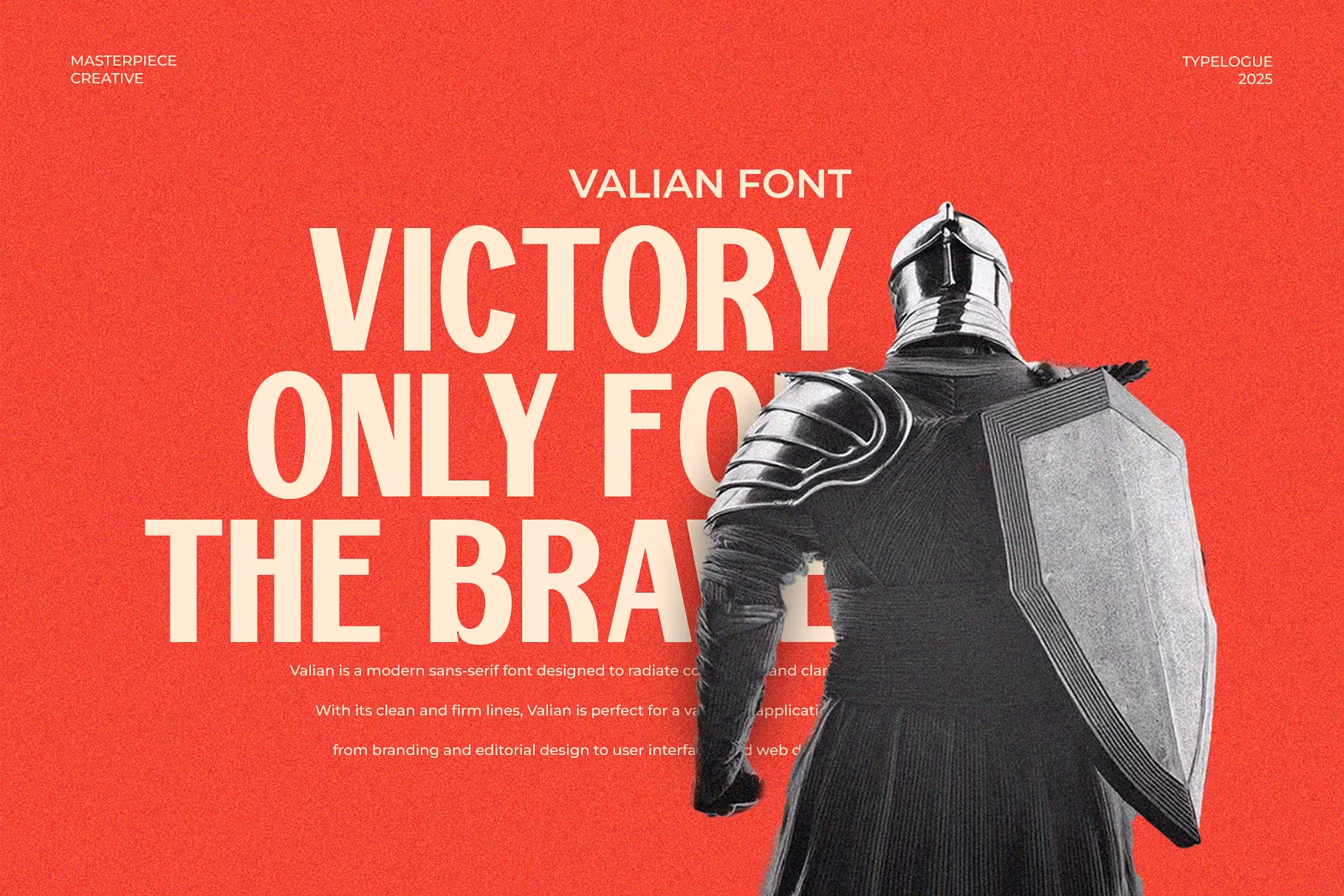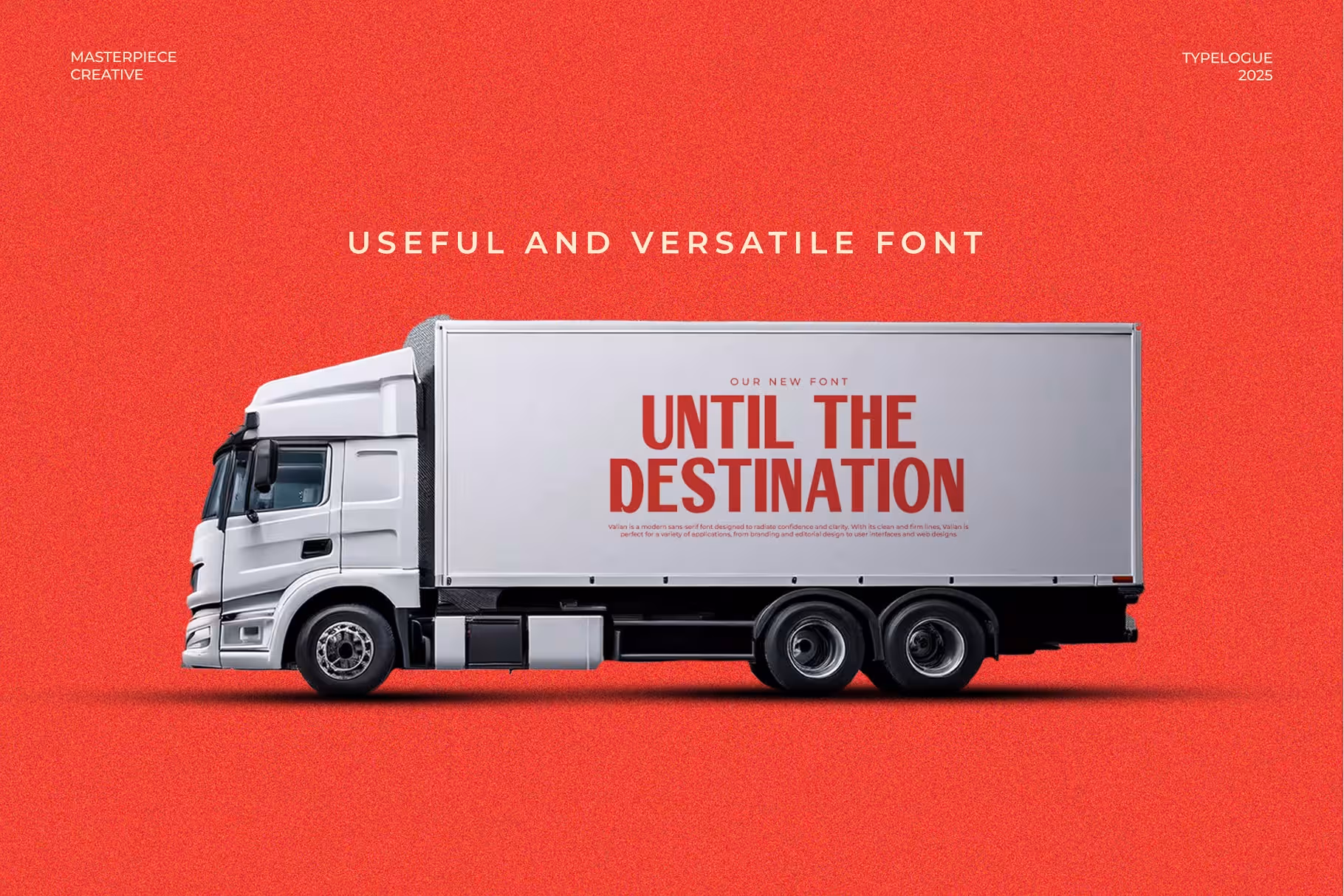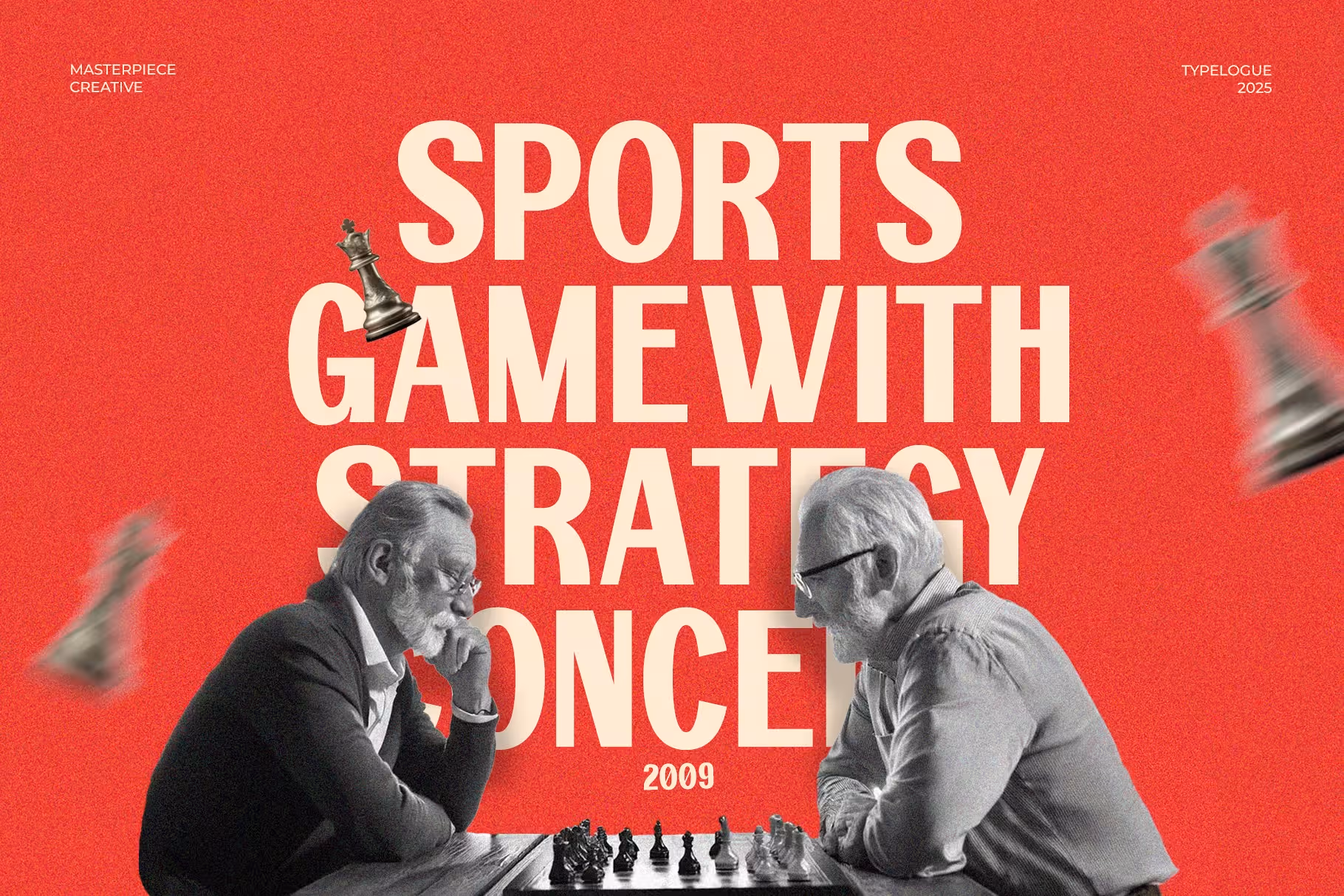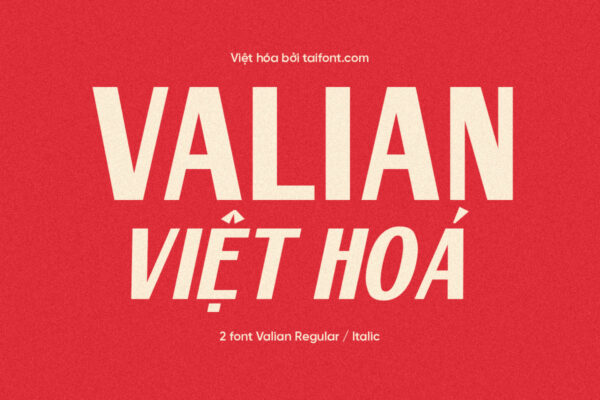
Giới thiệu về Font TF Valian Regular & Italic Việt hóa
TF Valian Regular & Italic Việt hóa là một bộ font chữ không chân (sans-serif) nổi bật với thiết kế mạnh mẽ, cứng cáp và mang phong cách cổ điển, gợi cảm giác về những bảng hiệu cũ kỹ, quảng cáo thời xưa hay những dòng chữ được in ấn một cách dứt khoát. Font này toát lên vẻ vững chãi, bền bỉ và đầy cá tính, lý tưởng để tạo điểm nhấn độc đáo và thu hút mọi ánh nhìn trong các thiết kế đòi hỏi sự mạnh mẽ và hoài niệm.
Với đặc điểm là nét không chân dày, chắc chắn và khả năng gợi cảm xúc mạnh mẽ về quá khứ, Valian là lựa chọn hoàn hảo cho các ấn phẩm muốn truyền tải sự độc đáo và phong cách:
- In ấn: Hoàn hảo cho các ấn phẩm in ấn đòi hỏi sự mạnh mẽ và rõ ràng như tạp chí, báo cáo, brochure, catalogue, hoặc danh thiếp. Độ sắc nét và chắc chắn của font giúp nội dung được truyền tải một cách hiệu quả, ngay cả trên nhiều chất liệu giấy khác nhau.
- Thiết kế tiêu đề: Lý tưởng để tạo các tiêu đề chính (headline), slogan, hoặc thông điệp quảng cáo trên poster, banner, hoặc bất kỳ ấn phẩm nào cần sự chú ý tối đa. Nét chữ mạnh mẽ của font giúp thông điệp của bạn nổi bật, dễ đọc và truyền tải một cách hiệu quả ngay từ cái nhìn đầu tiên.
- Thiết kế nhận diện thương hiệu (vintage): Phù hợp cho logo hoặc bộ nhận diện thương hiệu muốn truyền tải sự mạnh mẽ, cá tính và một chút hoài cổ đầy phong cách, đặc biệt là các thương hiệu liên quan đến đồ da, công cụ, hoặc các sản phẩm thủ công truyền thống.
- Poster và Banner: Đảm bảo khả năng đọc tốt ngay cả ở kích thước lớn, và tạo hiệu ứng thị giác mạnh mẽ khi in trên các chất liệu khác nhau như bảng hiệu, backdrop sự kiện hoặc các ấn phẩm quảng cáo.
Với TF Valian Regular & Italic Việt hóa, bạn có thể dễ dàng thổi hồn mạnh mẽ, sự độc đáo và cá tính vào các thiết kế, tạo ra những sản phẩm không chỉ đẹp mắt mà còn cực kỳ ấn tượng và có khả năng thu hút sự chú ý tối đa.